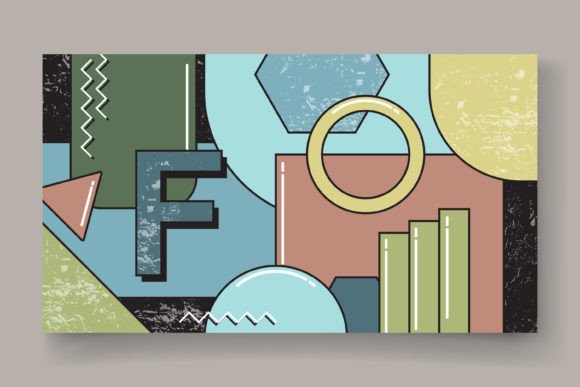
Stylish Font Pattern Set with Words
Mencari elemen reka bentuk yang sesuai boleh menjadi mencabar, tetapi Stylish Font Pattern Set with Words menawarkan koleksi luar biasa yang menaik taraf karya anda serta-merta.
Sama ada anda mencipta produk POD (Print on Demand), jemputan perkahwinan atau grafik media sosial, Stylish Font Pattern Set with Words amat bersesuaian.